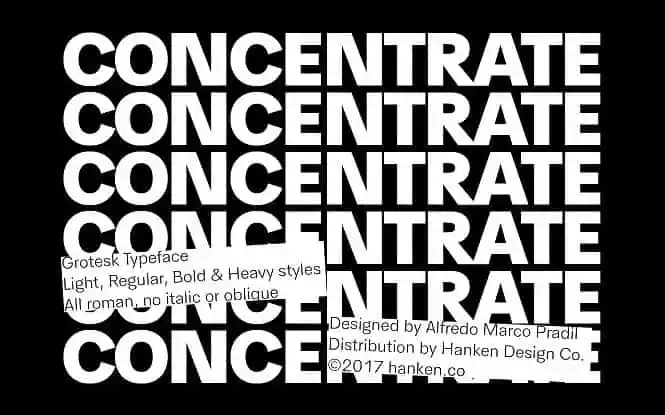
HK Concentrate Typeface é uma novidade que chega para simplificar sua jornada criativa sem sacrificar a qualidade. Desenvolvida pelo designer Hamilton, esta família de fontes sans serif oferece um toque geométrico com alguns detalhes intrigantes e personalizados. Afinal, não importa o número de palavras que você pode escrever com essas fontes; o que importa é sua capacidade de expressar-se de maneira assertiva e confiante. Ideal para quem busca mais produtividade na criação de trabalhos, HK Concentrate Typeface representa um passo além na jornada para encontrar a melhor combinação entre modernidade e criatividade.